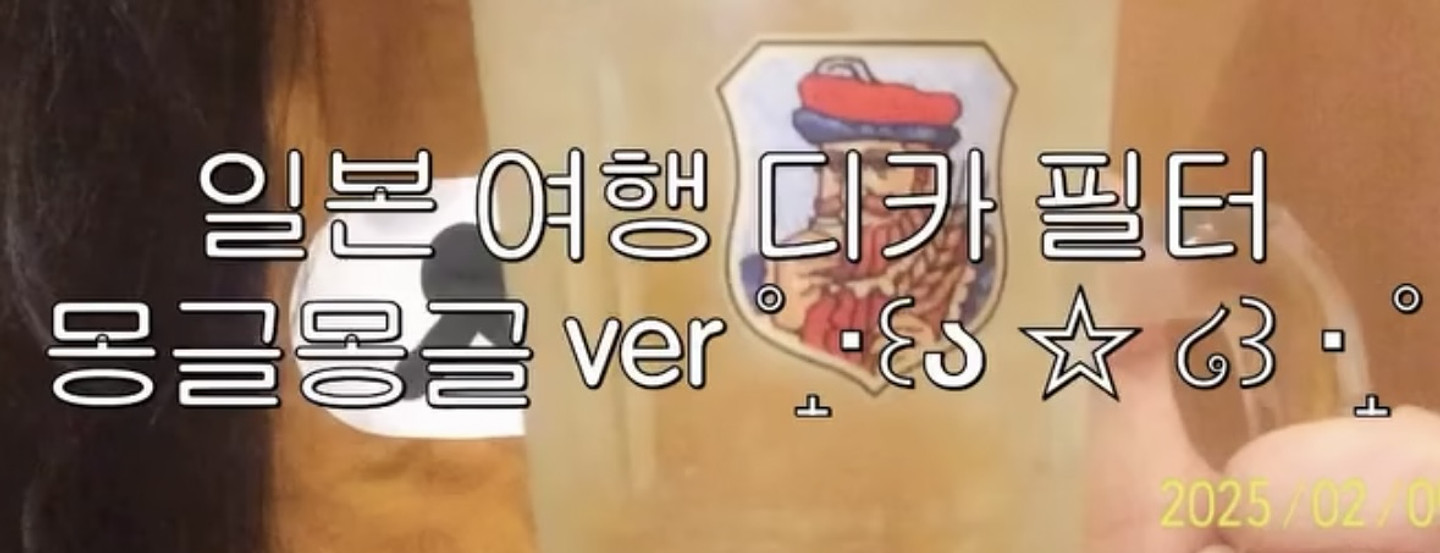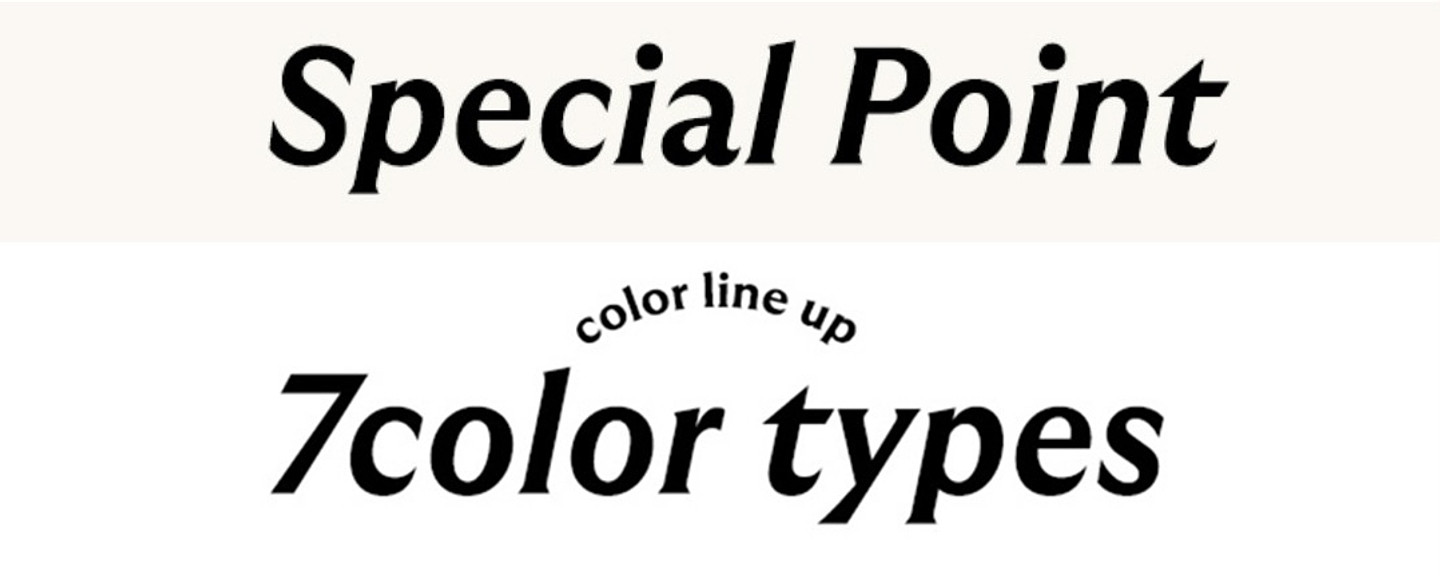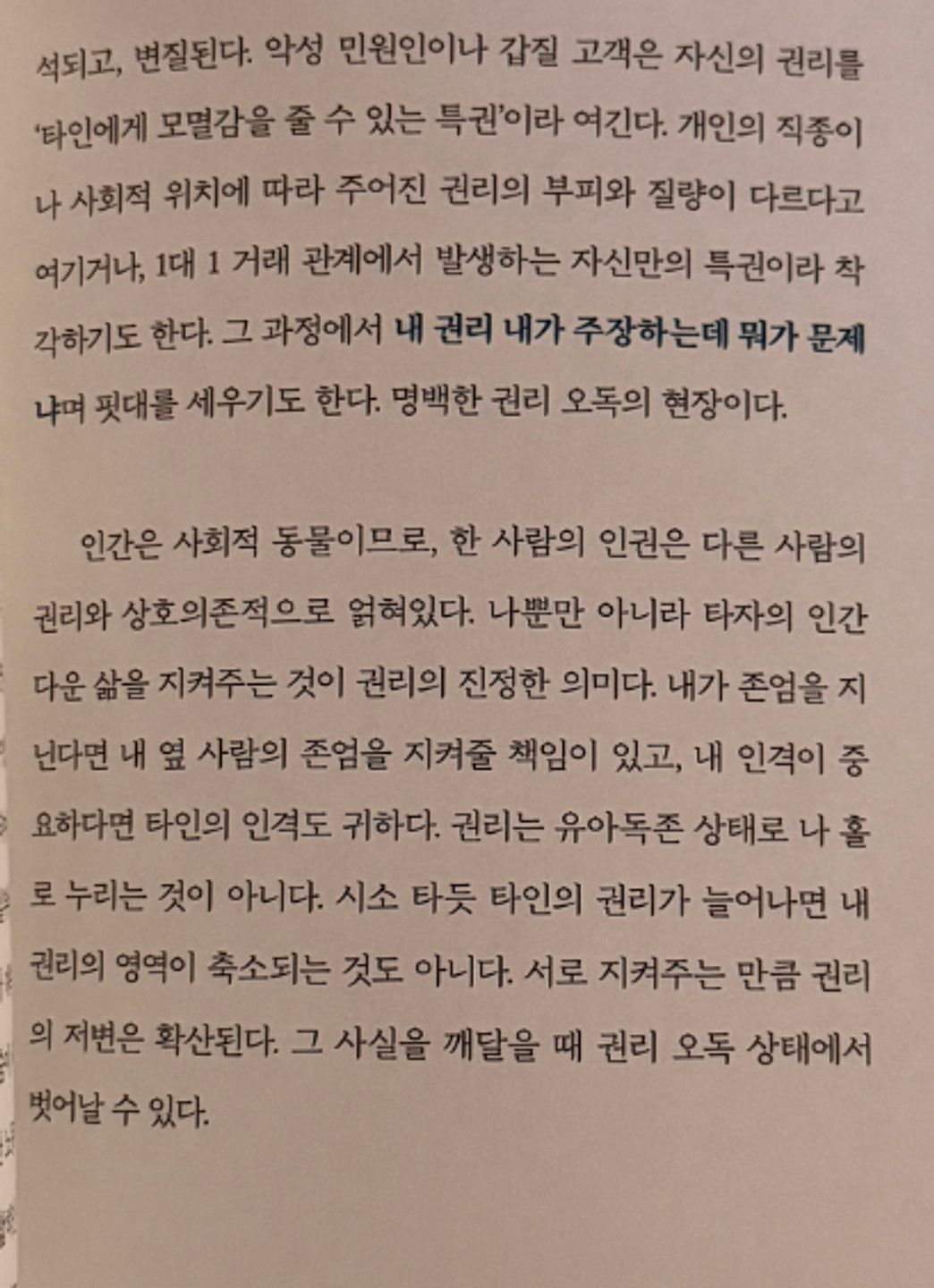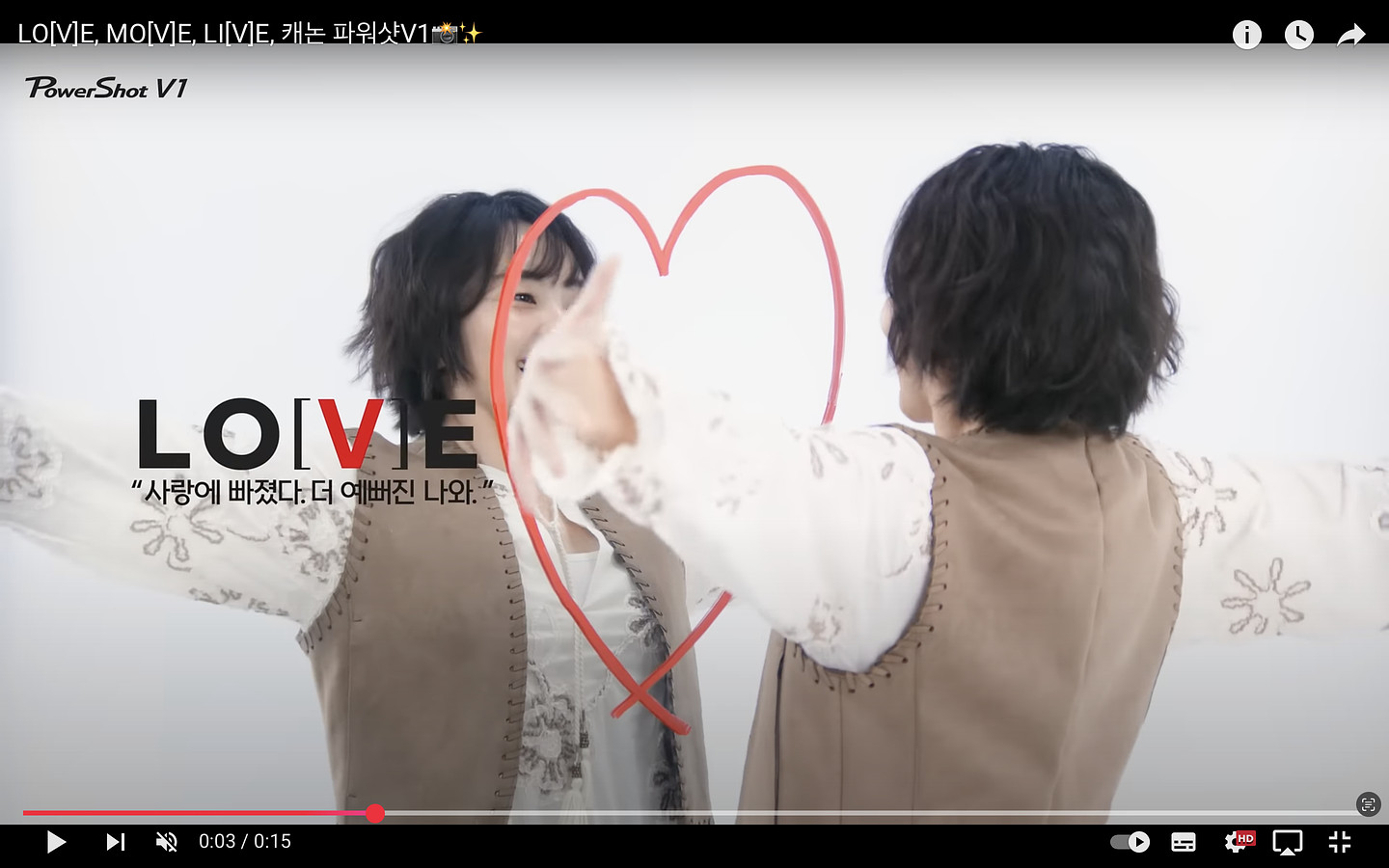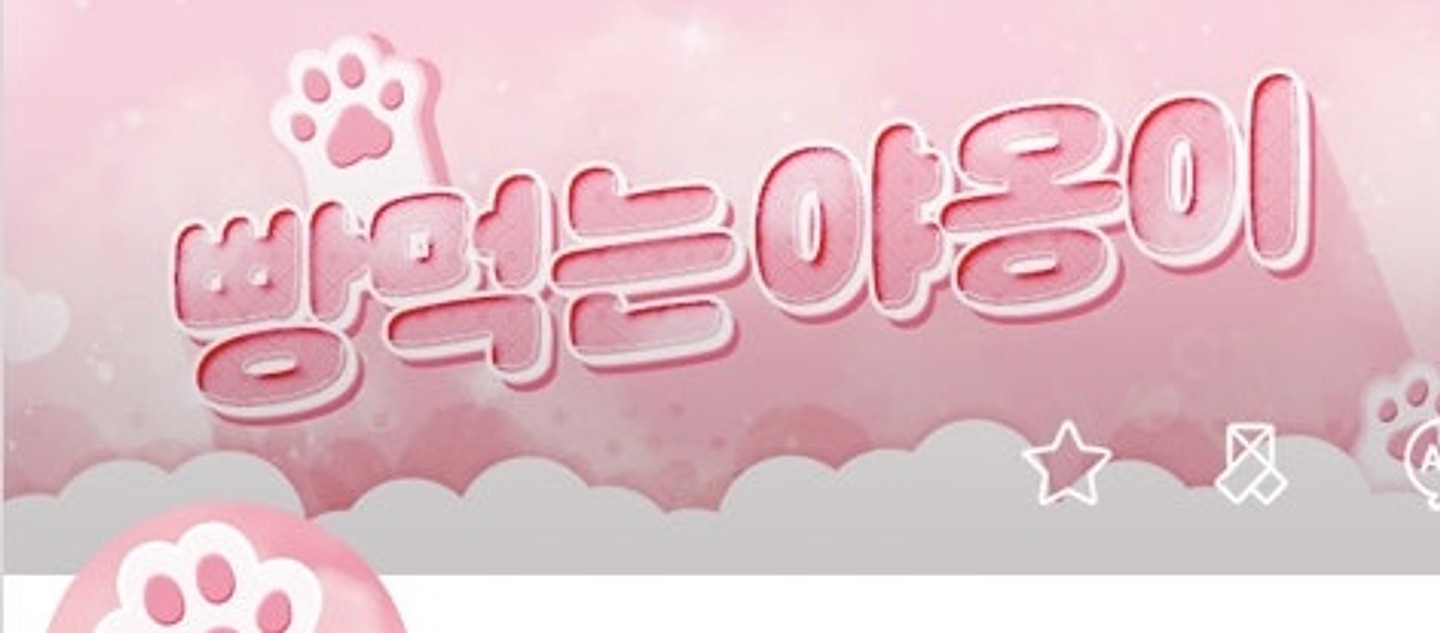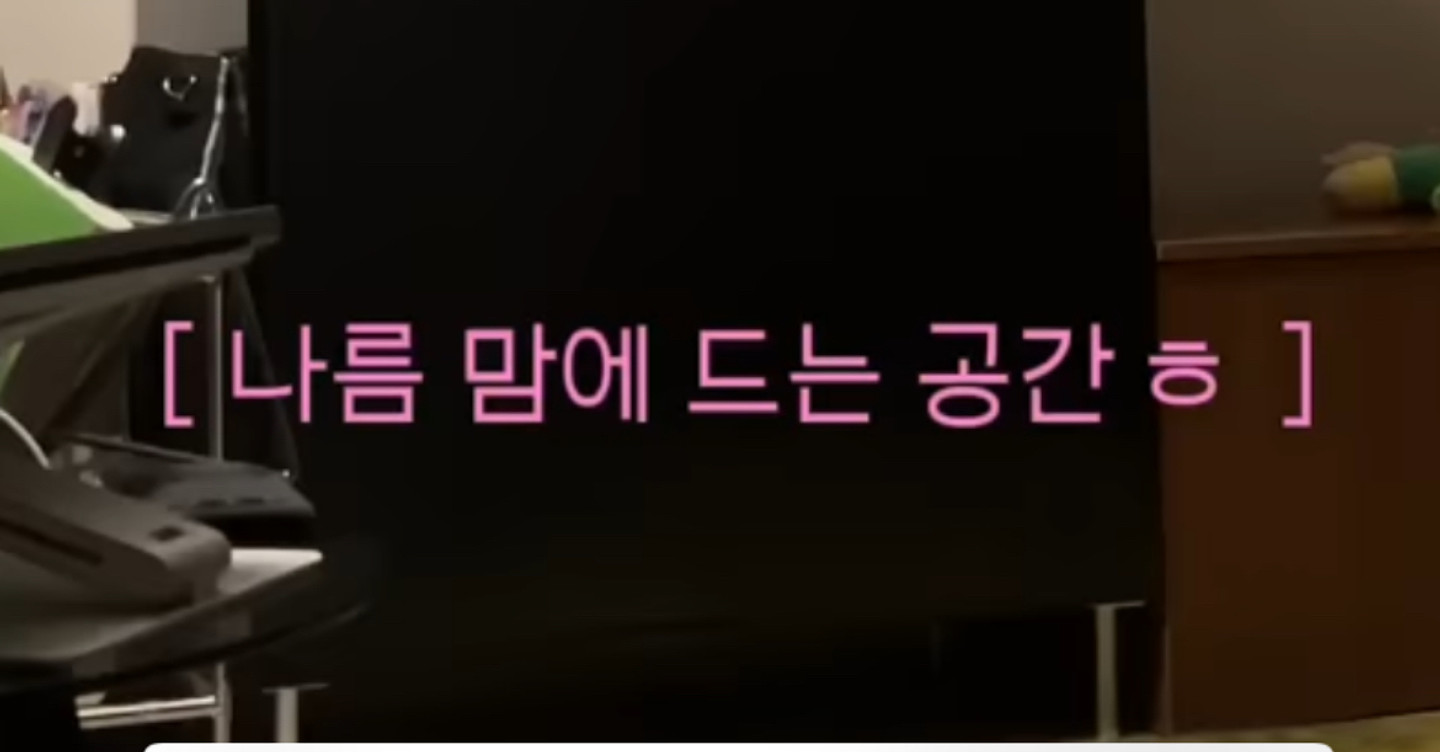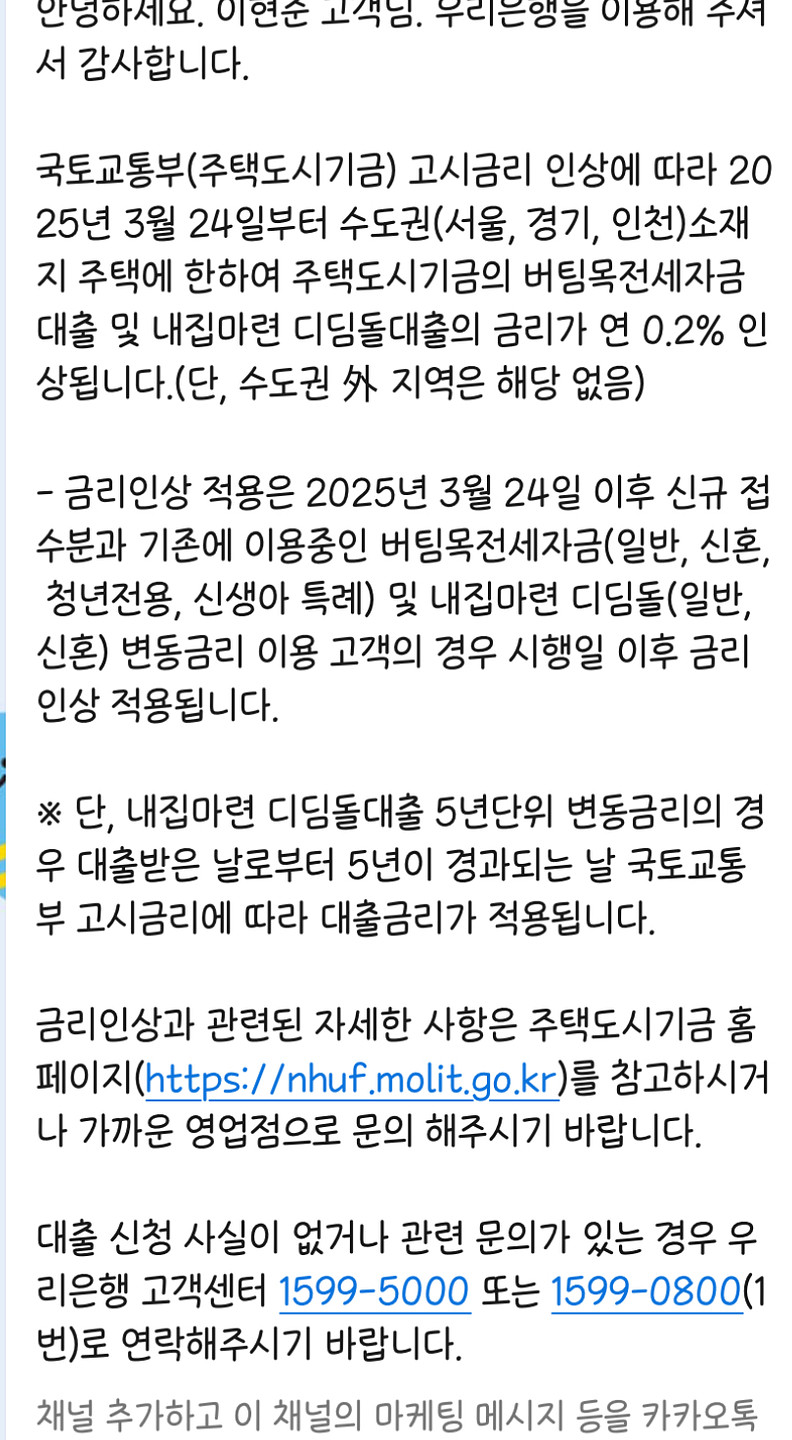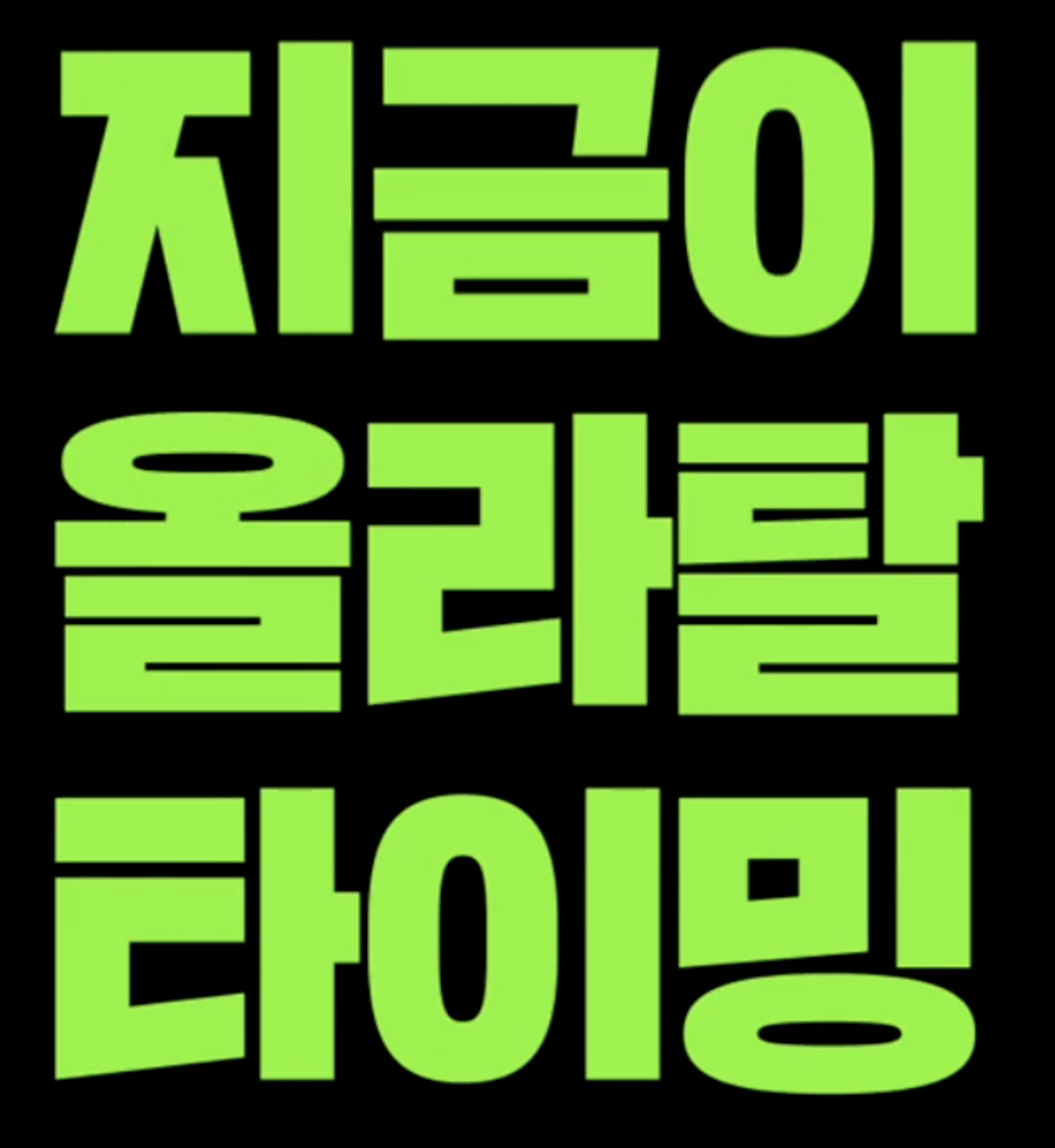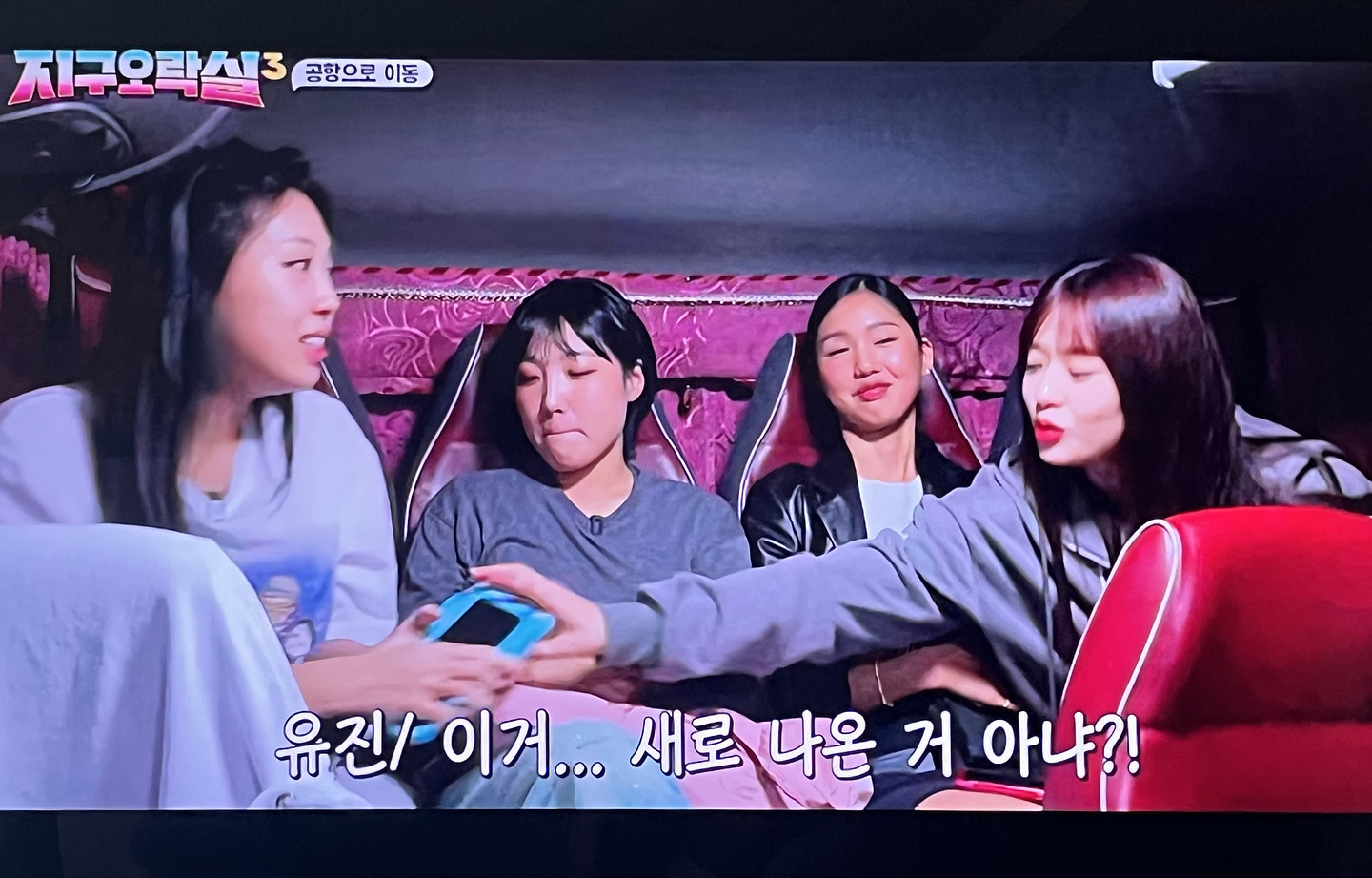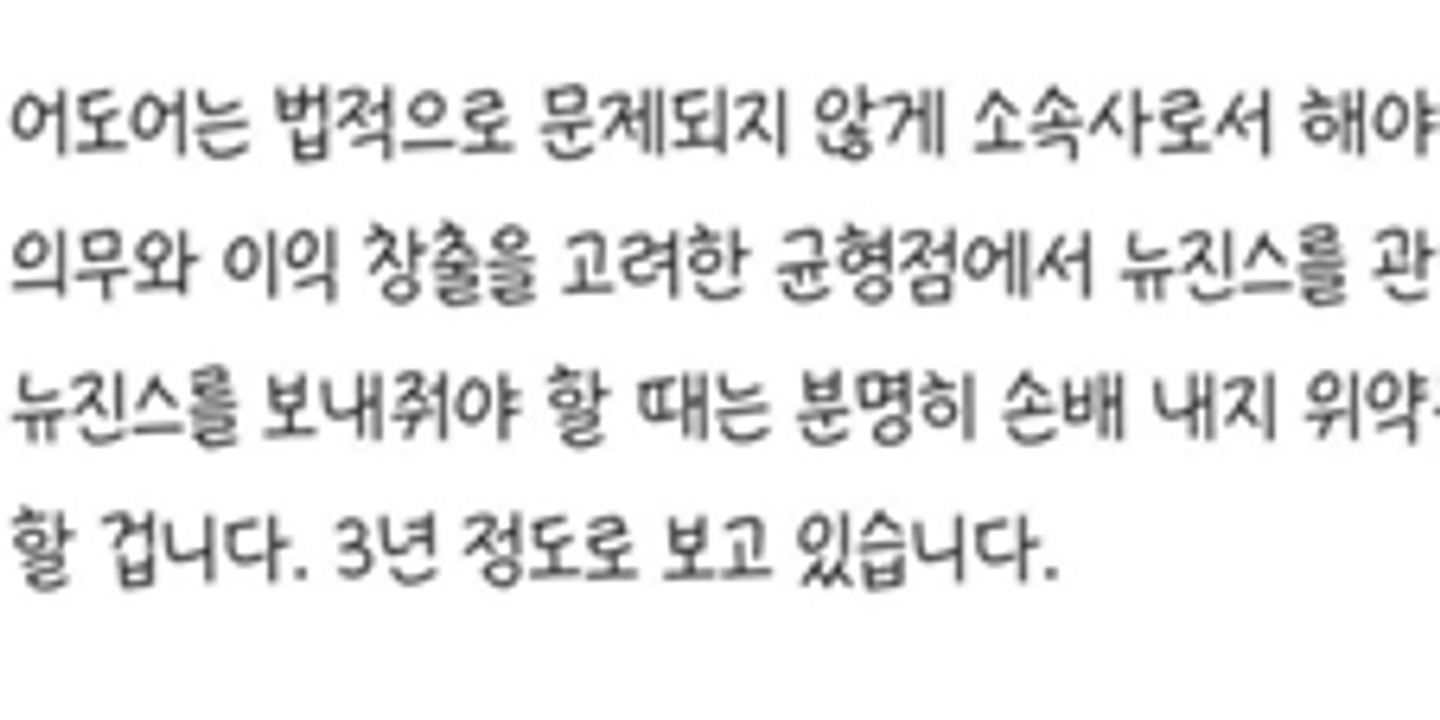
폰트궁금해요!!
이 폰트가 뭔지 알려주실수있으실까요 !!
짠한형보다가 폰트 궁금해서 여쭤봅니다! 1. 그 사람을~ 2. 아 저 J(?)라서요 3. TI를 잘 모르는~ 세 가지 폰트 궁금합니다. 알려주세요~~
폰트알려주세요
이 폰트는 어떤 폰트일까요?
급해요 진짜 이 폰트가 무슨 폰트일까요 제발
이 폰트 궁금합니다 ㅠㅠ
폰트 알려주세요!
폰트 찾아주실 분 계신가요 ㅠㅠ
이 글씨체 알려주세요~
이 글씨체 알려주세요~!
얇은 손글씨 느낌의 폰트 궁금해요!
손글씨 느낌의 폰트 궁금해요!
폰트 여쭤볼 슈 있을까요 ??
이 글씨체 혹시 아시나요? ㅠㅠ
이 폰트 이름 궁금해요
이 폰트 이름 뭔가요?
무슨 글씨첸가요?
무슨 폰트인가요? 학교안심 바른돋움은 아닙니다.
이 폰트 궁금해요.. 폰트사이트 여기저기 다 찾아봤는데도 못찾겠어요ㅠㅠ
트위터에서 봤는데 무슨 폰트인지 아시는 분 있나요?.?
요거 어떤폰트인가요…??
책 보다 폰트가 이뻐서 이름을 알고 싶어요ㅠ 정확한거 모르시겠으면 ㅇ(이응)이 별 모양으로 나오는 폰트 찾아주실 분 구해요!
폰트 아시는 분 계실까요?
사진에 나온 한글 폰트 이름이 궁금합니다.
이 폰트 알려주세요 😳
이건 무슨 폰트인가요?
폰트가 궁금해요... 이런 덜덜 떨리는 비슷한 폰트라도 추천해주시면 감사드리겠습니다..!
암수술후재활 365일 입원실운영 / 일광한방병원 서체 알려주세요!
with love 라고 적힌 폰트 아시는분 계실까요?
이거 무슨 폰트인가요 ?? ㅠㅠ
티키틱 유튜브에서 본 자막인데 폰트가 어떻게 되나요?
둥글둥글하고 뭔가 올록볼록해요
이거 무슨 폰트인지 아시는 분 계실까요..?
유튜버 아오니님 영상에 나오는 폰트인데 이름이 뭔지 알 수 있을까요
폰트가 뭔가요?
이 폰트 무슨 폰트인지 알 수 있을까요???
이 폰트 이름 알고 싶어요!
유튜브 "띱" 영상에서 쓰인 폰트입니다 무슨 폰트일까요?
Day 1 이랑 카메라도 켜놓고 실제로 잠들었습니다 폰트 궁금해용 새해 복 마니 받으세용
이 폰트 뭔가요ㅜㅜ
그림 속 두 가지 폰트의 이름을 찾아주세요 1. 주의사항, TBPE는 약물, 관련법령 2. 유아교육법 및 초중등교, 교원자격점검령 및 동령
이 글씨체좀 찾아주세요 갑자기 폰트가 바뀌어서 너무 답답합니다 ㅠㅜㅠㅜ
폰트 찾아주실 분 … 비슷한 폰트들은 봤는데 ㅇ 모양 같은 게 달라요ㅜㅜ 주워온 이미지라 이미지는 변경합니다!
트위터에서 본건데 폰트가 궁금해서요 아시는 분..?
무슨 폰트일까요???
이 폰트 이름이 멀까요...
이 폰트 뭘까요???
문학동네 장편소설 그림자 왕 영문 폰트 찾습니다
요즘 릴스에서 자주 보이는 폰트인데 무슨 폰트인지 궁금합니다ㅠ
이 지하철 폰트 뭔가요?